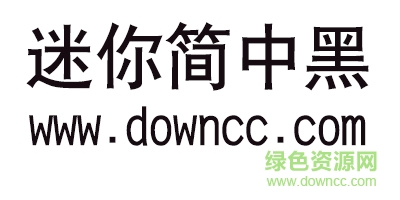
迷你簡中黑字體筆順和微軟黑體幾乎是一樣的,這款字體可以用進(jìn)行簡單的廣告設(shè)計排版使用。字體風(fēng)格比較中規(guī)中矩,喜歡的網(wǎng)友快來綠色資源網(wǎng)下載吧。
迷你簡中黑體是一款超有個性的迷你字體,安裝在電腦上之后能夠讓你擁有超個性化的字體!迷你簡中黑字體很適于標(biāo)語、標(biāo)題,使人重視;又因它結(jié)構(gòu)嚴(yán)謹(jǐn),筆劃單純,所以也常作為初學(xué)美術(shù)字練習(xí)的一種字體。
1.字體較粗,橫豎粗細(xì)一致
2.方頭方尾,點(diǎn)、撇、捺、挑、勾也都是方的
3.渾厚有力,樸素大方和引人注目